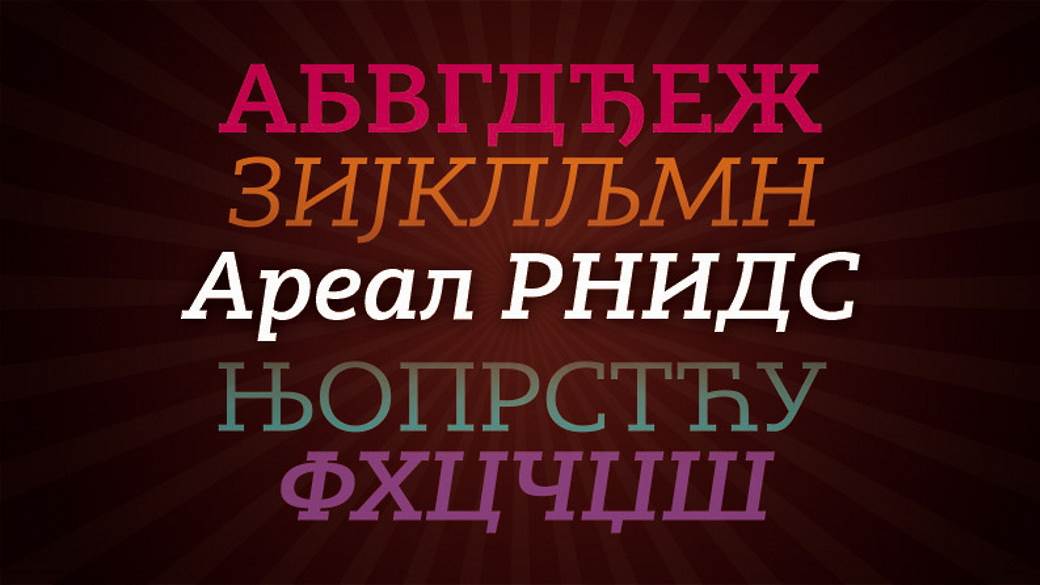
Srpska ćirilica tj. ćirilički fontovi na internetu dosad su najčešće bili manje ili bolje prilagođeni derivati ruskih fontova.
Iako je to za mnoge bilo prihvatljivo slova kakva su “g“, “d“, “p“ i “t“ često su, posebno u pisanom obliku pravila problem na internetu.
Zbog toga je bilo potrebno preduzeti mere da se stvori pismo ili porodica ćiriličkih pisama, koja su u skladu sa konvencijom srpske ćirilice. Ti fontovi moraju biti lako povezivi sa veb stranama i potrebno je da se dobro učitavaju.
Google kompanija je ponudila određene ćirilične fontove za internet i to nekoliko njih, ali su i oni svi uglavnom izvedeni iz ruskog pisma, mada se u praksi mogu pronaći i primeri izvođenja srpske ćirilice iz bugarskog pisma. Veliki problem sa kojim se naša ćirilica dosad susretala jeste činjenica da su na njoj radili stranci, odnosno na njenom prilagođavanju i izvođenju iz drugih pisama, što je posebno vidljivo u Microsoft Word i drugim Microsoft programima, zbog čega je bilo neophodno da domaći stručnjaci posvete vreme izradi srpskog ćiriličnog fonta zajedno sa svim njenim oblicima (kurziv i podebljan) u štampanom i pisanom obliku.
Areal RNIDS je novo ćiriličko pismo, koje se sastoji od četiri fonta, čiju je izradu omogućila Fondacija Registar nacionalnog internet domena Srbije (RNIDS) u saradnji sa udruženjem Tipometar, predstavljeno je 28. januara u Azbuci, u okviru zdanja Doma Vukove zadužbine. Autorka fontova je profesorka Fakulteta primenjenih umetnosti Olivera Stojadinović, a fontove je moguće besplatno preuzeti sa sajta RNIDS-a.
Ovo pismo pogodno je za upotrebu i u štampi i na internetu, iako je rađeno prevashodno imajući u vidu upotrebu na internetu.
Areal RNIDS kreiran kao slabserifno pismo sa četiri fonta, jer se slabserifna i sanserifna pisma najčešće koriste na internetu. Tokom izrade fonta kontinuirano je testiran digitalni prikaz, zbog čega se pismo izuzetno dobro prikazuje i čita na malim ekranima, kakvi su ekrani pametnih telefona putem kojih najčešće pristupamo internet sadržajima. Novo pismo pogodno je za sve digitalne sadržaje, za upotrebu u softverima za kreiranje i uređivanje teksta, uključujući i profesionalne softvere za tekst i grafiku.